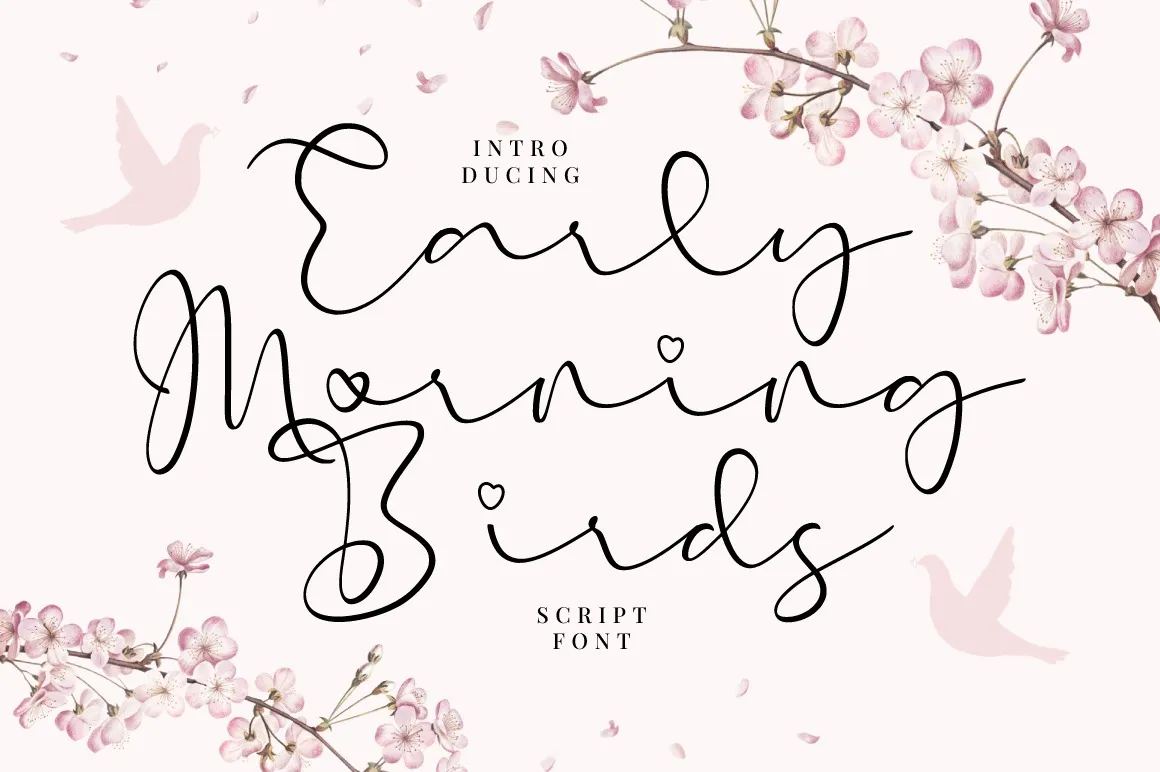
Early Morning Birds Font
A fonte Early Morning Birds é uma tipografia escrita à mão que captura a essência da natureza nas primeiras horas do dia. Desenvolvida pelo designer Tedyindrawan, essa font se destaca por suas formas desarranjadas e naturais, dando um aspecto realista incomparável. Perfeita para projetos de marca, logomarcas, designs de casamentos, postagens nas redes sociais, anúncios, embalagens de produtos, design de produtos, etiquetas, fotografia, marca d’água, convites e materiais de correspondência, a Early Morning Birds oferece um toque autêntico da escrita à mão. Ideal para qualquer projeto que necessite de um toque natural do estilo da escrita à mão. A cada traço e curvatura desta fonte, está presente o encanto e a serenidade das manhãs mais cedas.